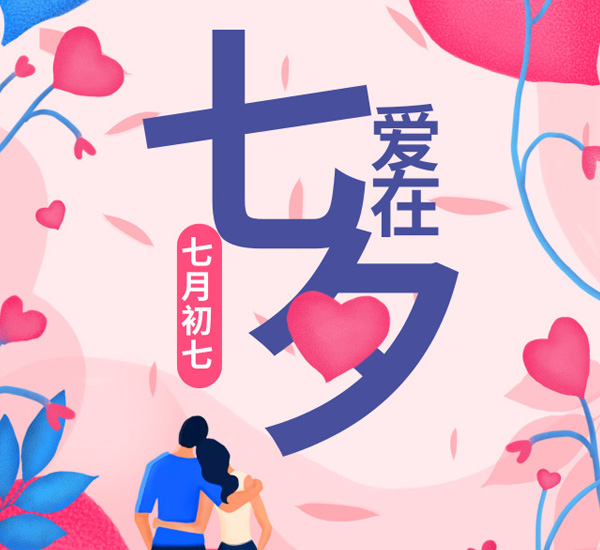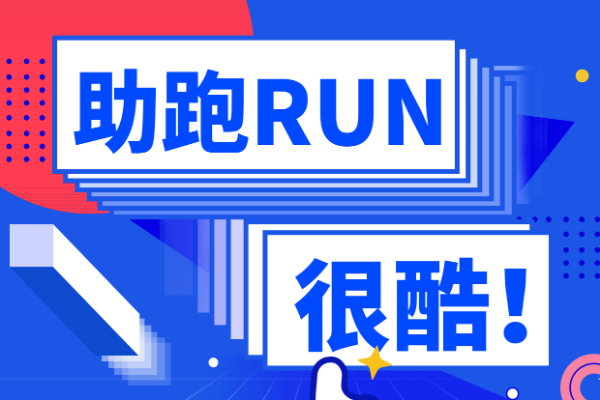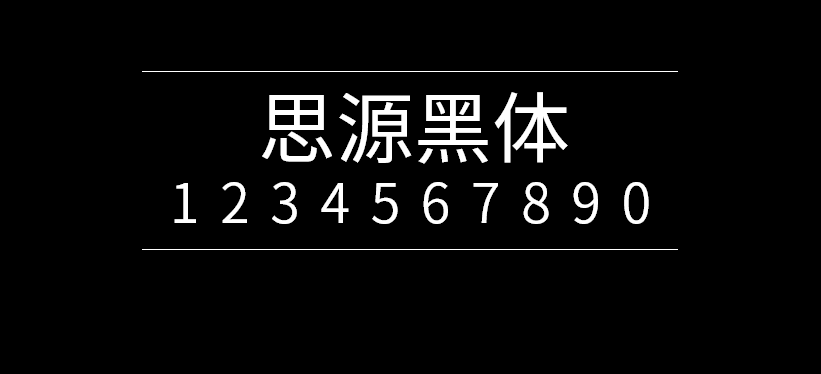
思源黑体-简体中文版
思源黑体是由adobe与谷歌领导开发的开源字体,从2014年至今经过不断的修正与完善,影响越来越大,像思源柔黑、思源真黑等字体就是此开源的基础上衍化而来的,实用性非常高。 有七种字体粗细(ExtraLight、Light、Normal、Regular、Medium、Bold 和 Heavy),完全支持日文、韩文、繁体中文和简体中文,还包括来自 Source Sans字体家族的拉丁文、希腊文和西里尔文字形共65536个字形。Google将其命名为Noto SansCJK,作为Google的Noto字体家族的成员。Adobe则命名为Source Han Sans,作为Adobe的Source字体家族的一员。Adobe拥有字体设计的版权。发布的字体文件则可以不受限制的免费使用。